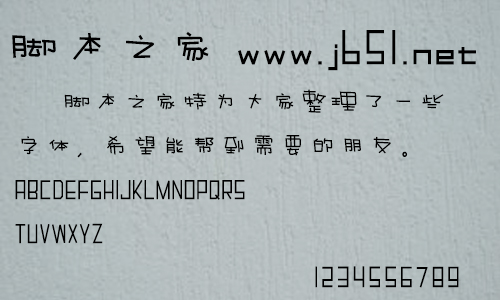
方正淘樂簡體是由方正字庫出品的藝術(shù)字體,字體的筆畫全部由等粗的直線段搭接而成,字形結(jié)構(gòu)夸張,字面大小不一,字內(nèi)空間充滿跳躍感,部分折筆處呈圓角.適合應(yīng)用于藝術(shù)設(shè)計(jì)、平面宣傳設(shè)計(jì)、網(wǎng)頁設(shè)計(jì),書法字帖等領(lǐng)域。